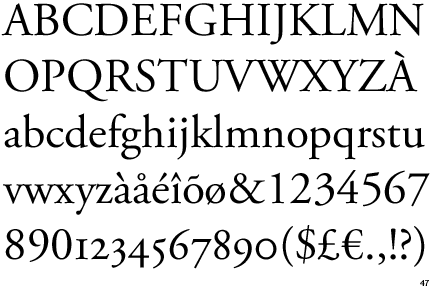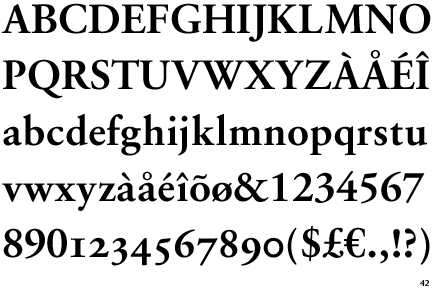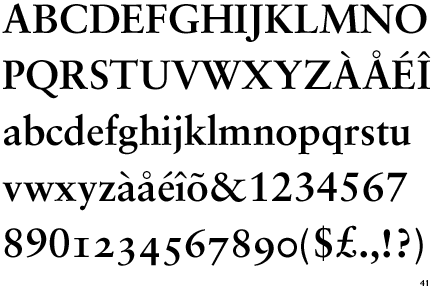
Runde Nullen in Kapitälchen von Antiquas
wenn ich die Kapitälchen einiger Antiquas so anschaue, frage ich mich woher diese runden Nullen eigentlich kommen? Was hat es damit auf sich, dass die Null (z.B. bei den meisten Garamonds) so Kreisrund gestaltet sind?
Für mich sieht das irgendwie seltsam aus. Vor allem wenn man im Text eine Zahl wie 200.000 setzt. Warum wurden diese nicht so gestaltet, dass die Strichstärken seitlich dicker sind und oben und unten schmaler? Wie z.B. bei der Albertina.
Adobe Garamond Pro:
Garamond96Bold:
Sabon Bold:
Ich meine mal irgendwo gelesen zu haben, dass die Null früher für "nichts" stand und so gar nicht geschrieben wurde. Als es dann aufgrund mathematischer Erfordernisse doch notwendig wurde, dieses "nichts" irgendwie richtig kennzeichnen zu können, brauchte man ein Zeichen ... ein vollwertiger Buchstabe wäre wohl der Idee von "nichts" nicht gerecht geworden, also ein einfacher Kringel/Punkt/Kreis, analog zu einem kleinen, unauffälligen kurzen Strich, der manchmal in einer Tabelle gesetzt wird, wenn die entsprechende Zelle einfach keinen Inhalt hat. Langsam hat sich die Null dann zu einem optisch dem lateinischen Alphabet angepassten Zeichen gewandelt.
Ich denke man braucht auch eine deutliche Unterscheidung zum ›o‹ ... :-?
Nein, mit dem O hat das nichts zu tun. Wi Sebastian ja schon angedeutet hat, hat sich das Zeichen einzeln entwickelt und stand eben symbolisch für »leeren Raum«. Zur Geschichte siehe auch hier: http://de.wikipedia.org/wiki/Null
Die kreisrunde Form ist also eher die ursprüngliche, die sich im Laufe der Jahrhunderte abgeschliffen hat und nach mit dem Duktus der anderen Ziffern vereinheitlicht wurde – insbesondere bei den Versalziffern. Bei Minuskel-/Kapitälchenziffern kann man diese historische Form noch besser unterbringen und das wird eben auch immer wieder gern gemacht.
Wobei ich doch finde, dass es aus ästhetischer Sicht im Text schon sehr seltsam aussehen kann.
Im Fontblog hatte Jürgen Siebert zur Frage nach der kreisrunden Null das hier geschrieben.
Gerade bei dem Buch, um das es bei dem Fontblog-Eintrag geht, sieht es wirklich eher nach einem Zwiebelfisch aus (siehe hier Seite 7 im PDF).
Es könnte auch was damit zu tun haben, daß sie ursprünglich eher als mathematisches Zeichen und nicht als Ziffer wahrgenommen wurde, und die mathematischen Zeichen sind ja alle geometrisch gebildet, und haben nicht den normalen Duktus. (Ist nur eine Vermutung von mir.)
Könnt ich mir auch gut vorstellen ... Schließlich hat man hier bis ins Mittelalter Römische Zahlen verwendet, die Null war also ein ganz neues Prinzip ...
auch nach dem Verfall des römischen Imperums wurden die sogenannten römische Ziffern (zum Beispiel zum Festhalten von Mengen im Handel) oder Adaptionen von diesen weiterhin verwendet. Eine Null ist in diesem System nicht vorgesehen. Unter anderem deshalb konnte damit auch nur sehr umständlich gerechnet werden.
Da war man im arabischen Raum (ausgehend von Indien) erheblich weiter! Mit den indisch-arabischen Ziffern (ab dem 3.Jahrhundert v.Chr.) wurde die komplexe Mathematik und moderne Naturwissenschaften überhaupt erst möglich. Mit diesem System konnten die Inder mit nur 10 Zeichen beliebig große Zahlen schreiben. Das Zeichen für Null (Nichts) war ursprünglich nur ein Punkt oder ein kleiner Kreis, also ein Platzhalter mit der Bedeutung Leere, Fehlen, Nichts. Die Vorstellung vom Nichts passte aber nur sehr schwer ins christliche Weltbild (wo das [ewige] Leben ja selbst nach dem Tod mit dem Paradies/der Hölle weitergeht).
Die genialen indischen Ziffern wurden schnell von anderen Völkern Asiens übernommen. Im 8.Jahrhundert entdeckten auch Araber auf ihren Kriegszügen die indischen Ziffern.
Europäische Ritter lernten dieses praktische Zahlensystem bereits während der Kreuzzüge kennen. Um ca. 1200 n.Chr. breitete sich das indisch-arabische System über Marokko, Spanien und Italien langsam in ganz Europa aus.
Leonardo Fibonacci verwendete 1202 zwar in seinen Werk »Liber abaci« die Null, allerdings bezeichnet er sie dort als Zeichen statt Zahl.
Viel später erst (ab dem 17. Jahrhundert) setzt sich die Verwendung der Null im praktischen Rechnen durch, also zu einer Zeit, als die Typografie in Europa schon auf eine lange Tradition zurückblicken konnte. Erst als die Null also auch als Ziffer statt Symbol akzeptiert wurde, wurde diese formal auch den restlichen Ziffern angepasst. Deshalb ist in vielen Schriften mit historischen Vorlagen (vor allem in Schriften des Typus Renaissance Antiqua) noch eine Null mit dem damals üblichen Aussehen enthalten.
Mir persönlich gefällt dieser Kreist aber auch nicht besonders gut. Ich habe im beim Setzen mit derartigen Schriften schon öfters mir selber eine individuelle Null zusammengebastelt.
Um die Mediäval-Null von einem Minuskel-o zu unterscheiden, sind die Nullen häufig in der Breite oder der Höhe zu den Kleinbuchstaben verschieden. Einige Schriften haben bei der Null die Schattenachse um neuzig Grad gedreht oder sonstwie anders ausgerichtet. Andere geben der Null nur einen einseitig geschwollenen Bauch. Die 1530 Garamond von Tiro Typeworks bietet neben der Scheiben-Null noch eine Alternativ-Null im SC-Schnitt. Bei der Herb und der Kompakt ist der Unterschied mehr als deutlich. Die Null der Spira hat schon fast Schwabacher-Charakter.